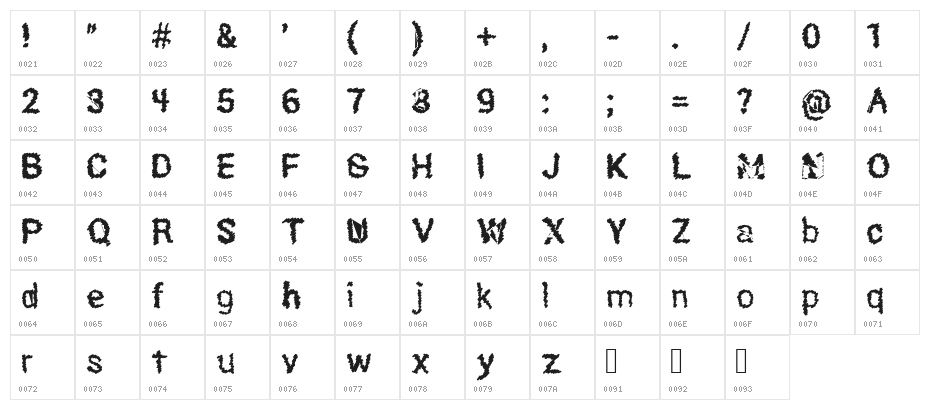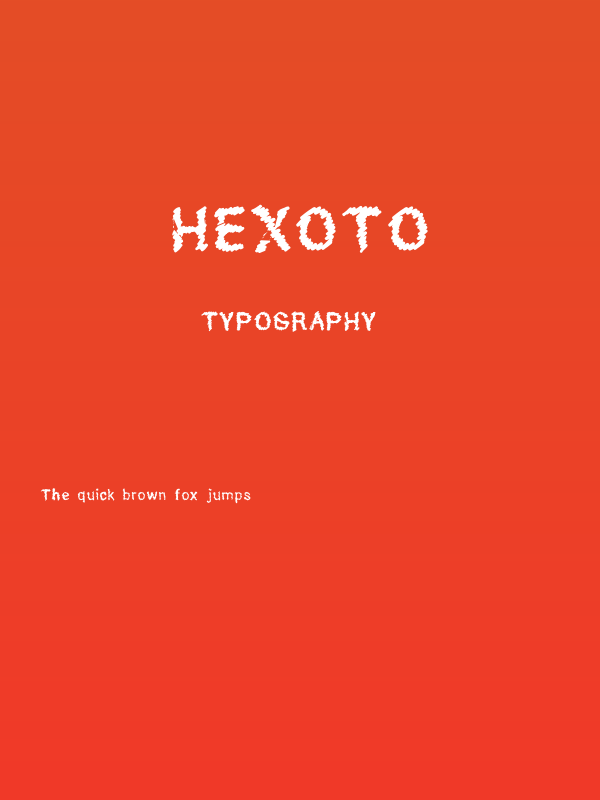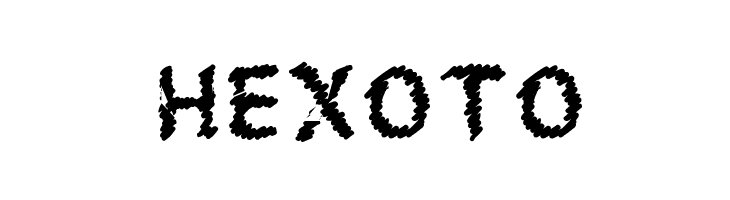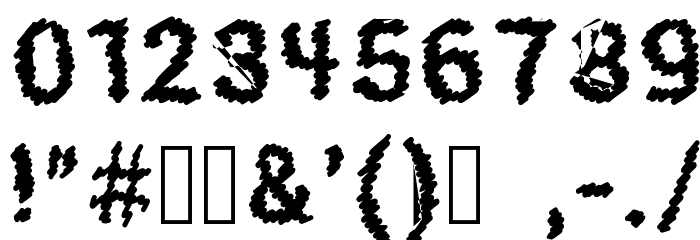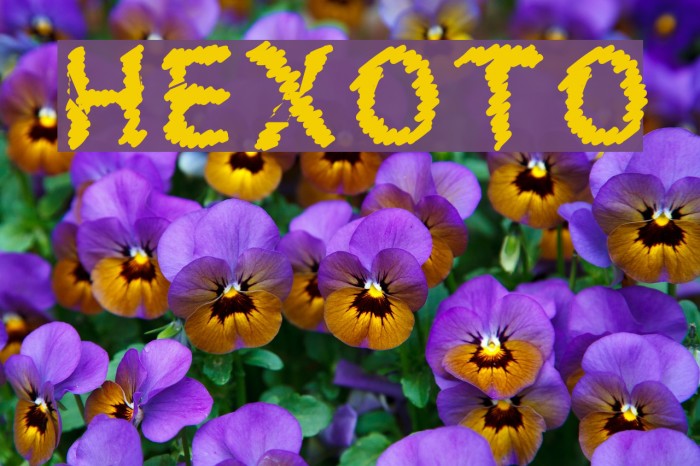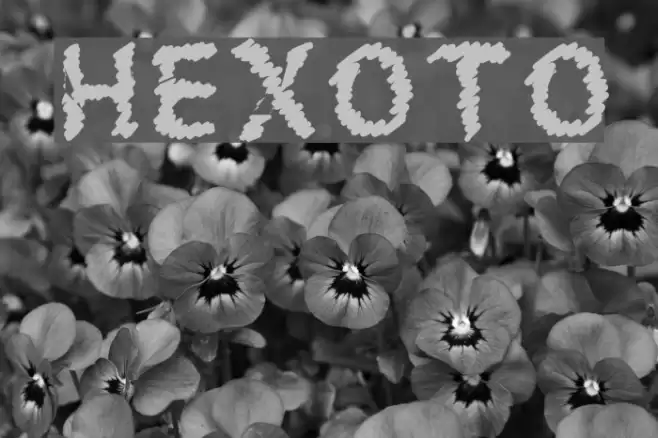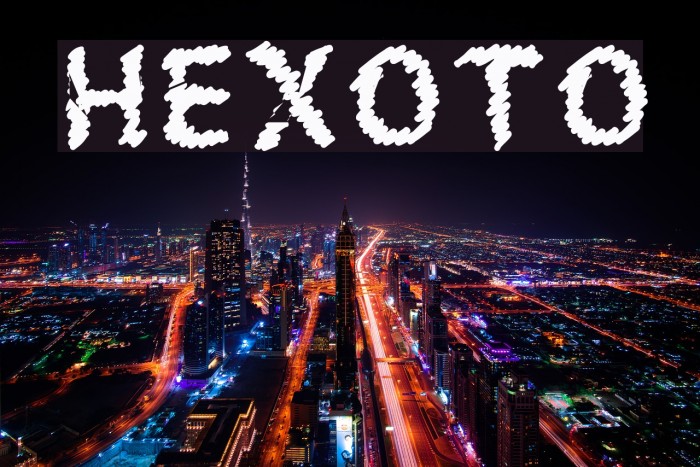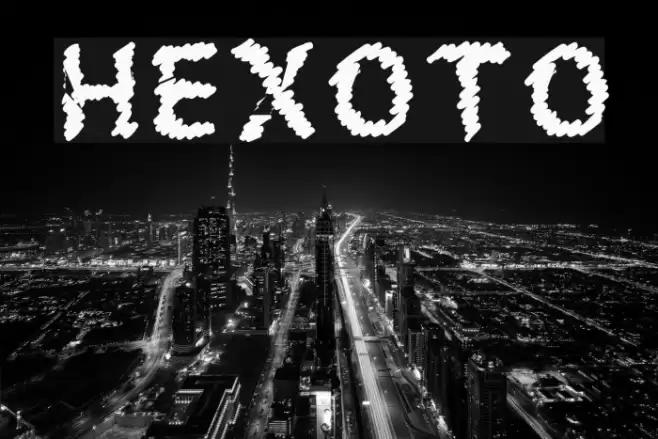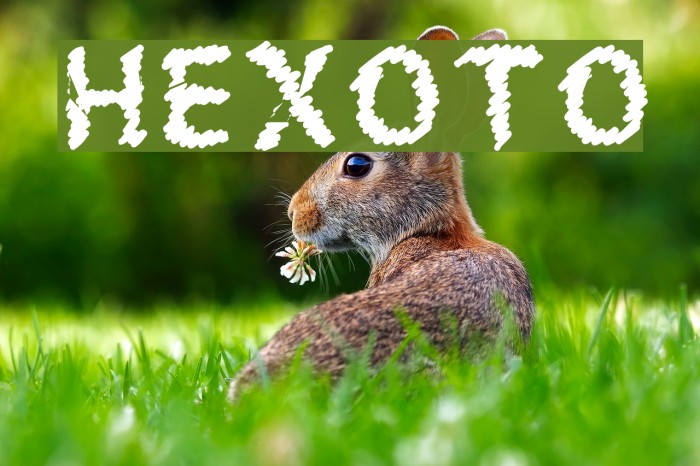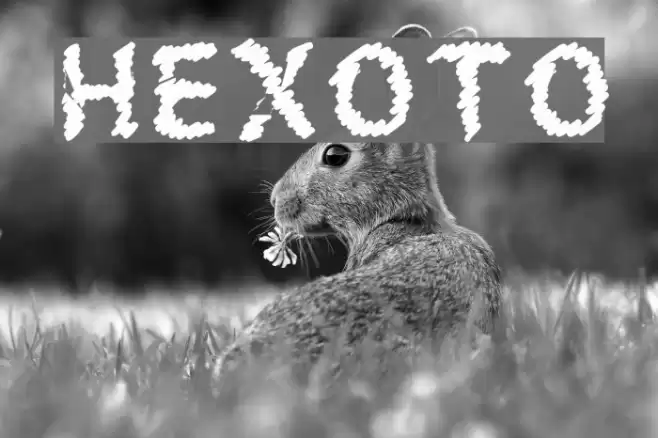
HEXOTO Font
✎ Distorted Eroded
| Projetos propostos | Ideal for album covers, posters, branding for edgy or alternative products, and any design needing a bold, artistic flair. |